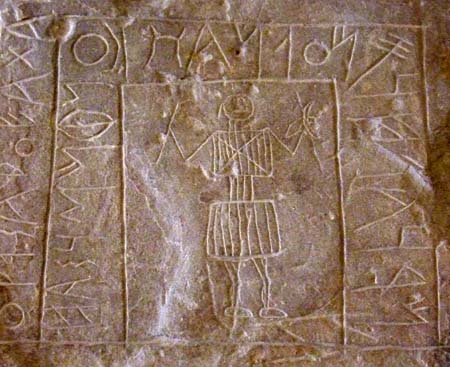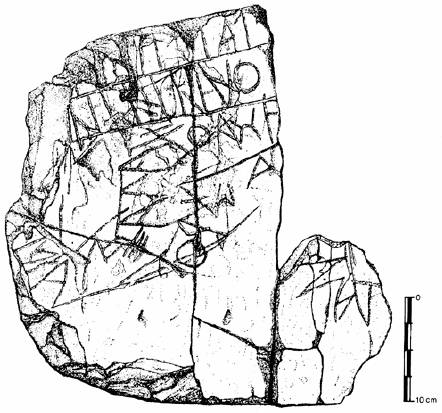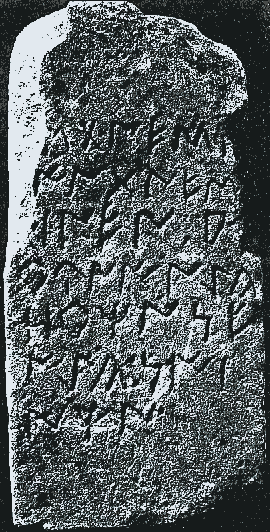
Os primeiros alfabetos em território português
É para o século vi a.n.E. que se data o uso dos primeiros sistemas de escrita com base fonética na Península Ibérica.
Escrita do Sudoeste
A Estela da Abóbada, achada no sítio arqueológico de Gomes Aires, em Almodôvar, é uma das poucas com figuração. No centro, emoldurado pelas bandas com glifos, vemos um guerreiro armado, em pose agressiva. Muitas das estelas com Escrita do Sudoeste provêm do Baixo Alentejo e puderam ser datadas – aproximadamente –, a partir das necrópoles conhecidas.
Estas necrópoles tinham inicialmente túmulos circulares e depois elaborados em forma rectangular. As datas destes monumentos funerários oscilam entre os séculos VII e V a.n.E. Esta estela esteve exposta longos anos no Museu de Beja e transitou para Almodôvar. Documenta o primeiro sistema alfabético usado em Portugal.
Este facto é de importância, pois em muitas outras etapas de evolução Pré-História –> História, o uso da escrita acompanha o desenvolvimento do urbanismo, da economia mercantil e da plena evolução das classes dirigentes e elitistas.
Contudo, em território ibérico, estes processos foram iniciados já muito antes, no Calcolítico (3.000 – 2.000 a.n.E.), mas não foram acompanhadas pelo aparecimento de um sistema de escrita. Esta teve que ser importada, muito mais tarde, do Mediterrâneo.
A chamada Escrita do Sudoeste ou Tartéssica ou Sudlusitana, da I. Idade do Ferro no Sul de Espanha e Portugal, foi desenvolvida pelos Tartessos, nome pelo qual os Gregos conheciam a civilização que se desenvolveu nas zonas das actuais regiões da Andaluzia, da Extremadura espanhola, do Baixo Alentejo e do Algarve.
Não é consensual a designação da primeira escrita na Peninsula ibérica. Para muitos historiadores é a Escrita do Sudoeste (SO) ou sud-lusitana. Os linguístas utilizam as designações de escrita tartéssica ou turdetana.
Estela com Escrita do Sudoeste
Estela funerária, com escrita ibérica do Sudoeste.
As inscrições conhecidas foram maioritariamente achadas nas áreas mais acidentadas entre o Alentejo e Algarve (em especial a Serra do Caldeirão), no território das nascentes dos cursos de água desta região (Sado, Mira, Arade) e dos três subsidiários do Guadiana (ribeiras de Oeiras, Vascão e Foupana).
Contudo, devemos salientar que desde as prospecções arqueológicas do casal de arqueólogos alemães Georg e Vera Leiser, nunca mais se fez uma prospecção e inventarização arqueológica sistemática em Portugal.
Os glifos do alfabeto da Escrita do Sudoeste (veja tabela) são claramente derivados de escritas fenícias. O sistema teria basicamente 27 signos, o número que se regista num monumento aparecido em Espanca (Castro Verde, Beja); esta inscrição mostra um abecedário gravado por alguém que possuía destreza e outro imitado, por baixo, por um aprendiz.
Estela de Neves II (segundo Maia e Maia, 1986, p. 30).
Os glifos são semelhantes aos alfabetos fenícios. Nos conjunto de glifos de Espanca, os primeiros catorze tem formas e valores fonéticos idênticos. Os cinco glifos que se seguem, embora apresentem um traçado semelhante, podem corresponder a fonemas diferenciados. Os últimos oito consideram-se relativamente independentes, adoptados para suprir a falta de glifos que completassem o sistema.
Sem contar com as variantes de algumas letras, conhecemos hoje cerca de 40 glifos diferentes. O que é que nos transmitem? A escrita, analisada por arqueólogos diletantes, foi considerada «complexa» e «indecifrável», mas o facto é que tem sido decifrada, pouco a pouco; a sua leitura é hoje parcialmente possível.
Conhecemos mais de oitenta textos, muitos que são fragmentos, quase todos gravados em placas do xisto que abunda na área da sua difusão.
Podemos «ler» uma boa parte das sequências gravadas nas inscrições, mas é problemático o conteúdo. O que significam?
Pouco sabemos sobre a(s) língua (s) em que estão escritas. Sendo a linguagem desconhecida, as dificuldades de interpretação dos textos são grandes, agravadas por ser díficil isolar palavras, pois quase sempre faltam separadores.
Contudo, já temos um primeiro repertório de sequências de glifos, que podem corresponder a «palavras». Já se pode sugerir correspondências com nomes conhecidos de origem indo-europeia. Um conjunto de inscrições funerárias apresenta no final uma sequência de glifos, com ligeiras variantes. Será uma fórmula do tipo «aqui jaz»?
Estela de Santa Perpetua de la Moguda
A comparação com línguas conhecidas fundamenta esta hipótese, e é uma base para a inclusão dos textos do idioma representado nas línguas indo-europeias. Pelo âmbito geográfico, admitiu-se a ligação com vestígios toponímicos da região.
Neste contexto se integram, por exemplo, os nomes de lugar terminados em -ipo (a que pertence a cidade andaluza de Ventipo, mas também Olisipo, Lisboa) e em -oba l-uba (onde se inclui o nome de Faro, Ossonoba, bem como o de Corduba).
Rodríguez Ramos, Jesús. La lectura de las inscripciones sudlusitano-tartesias. Faventia 22/1, pp. 21-48. 2000. PDF em http://ddd.uab.es/pub/faventia/02107570v22n1p21.pdf Rodríguez Ramos, Jesús, El Origen de la Escritura Sudlusitano-Tartesia y la Formación de Alfabetos a partir de Alefatos, Rivista di Studi Fenici, pp. 187-222, vol. XXX, 2, Consiglio Nazionale delle Ricerche, Roma, 2002. Soares, A.M.M. Povoado da Misericórdia (Margem esquerda do Guadiana, Serpa). Ocupações humanas e vestígios metalúrgicos. Vipasca. Aljustrel. 5, p. 103-116. 1996. Untermann, Jürgen. Zum Stand der Deutung der ‘tartessischen’ Inschriften. In: Eska, J. F. ; Gruffydd, R. G.; Viana, A. (1946) - Museu Regional de Beja. Arquivo de Beja. Beja. 2, p. 3-33. 1995. Schmoll, Ulrich. Die südlusitanischen Inschriften. Wiesbaden, 1961. Untermann, Jürgen. Monumenta Linguarum Hispanicarum. IV Die tartessischen, keltiberischen und lusitanischen Inschriften, Wiesbaden. 1997. Sauren, Herbert; A. Sidarus, As lápides de escrita ibérica do Museu Regional de Beja - Leitura e tradução. Arquivo de Beja, Actas das III Jornadas / Congresso, tomo I, Beja, 2005, 169-190. Sauren, Herbert; (A)Y, Island, Isolated Place. The Word in Punic and Iberian Inscriptions, Boletín de la Asociación Española de Orientalistas, Madrid, 41, 2005, 279-286. Sauren, Herbert. The Iberian inscriptions deciphered. Internal proves, El Periodo Orientalizante. Actas del III Simposio Internacional de Arqueología de Mérida: Protohistoria del Mediterráneo Occidental (2003). CSIC, Instituto de Arqueología, Mérida, Anejos de AEspA 35, 2005, 519-534.